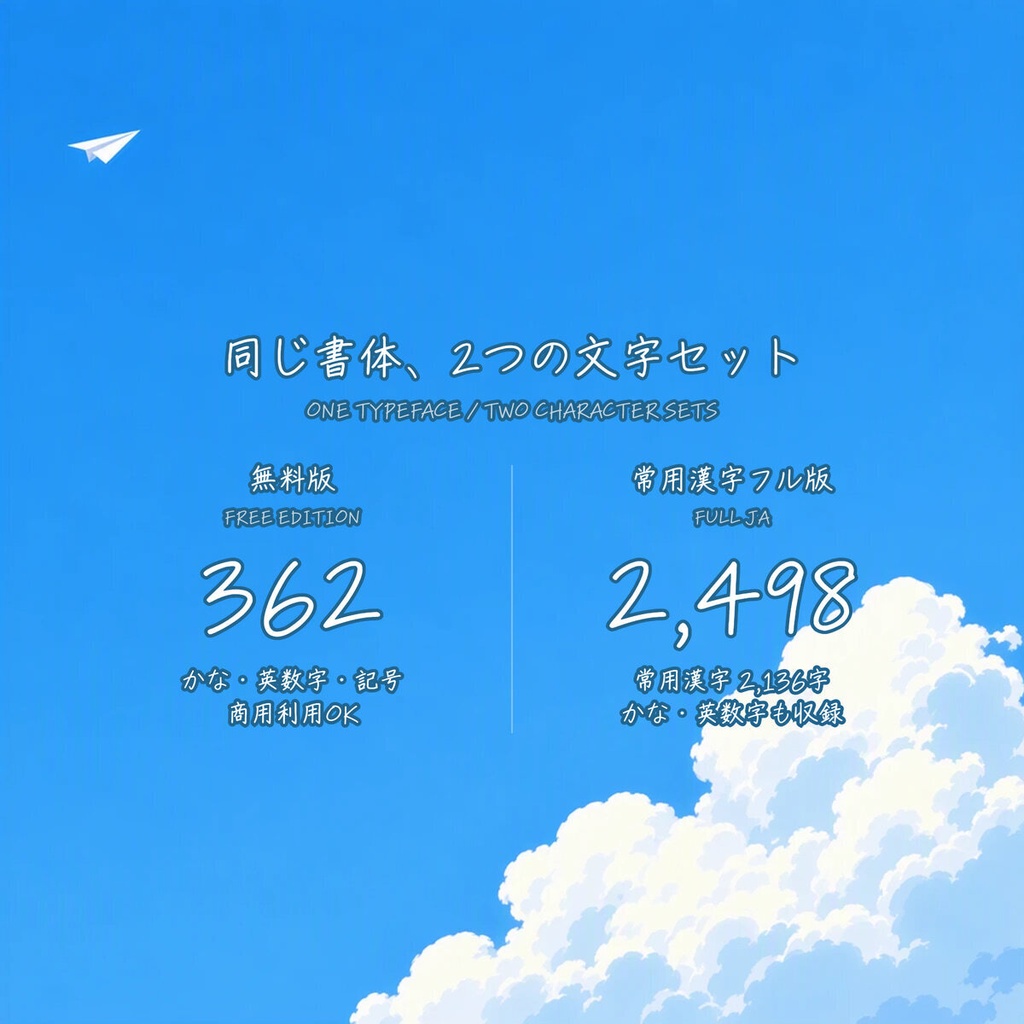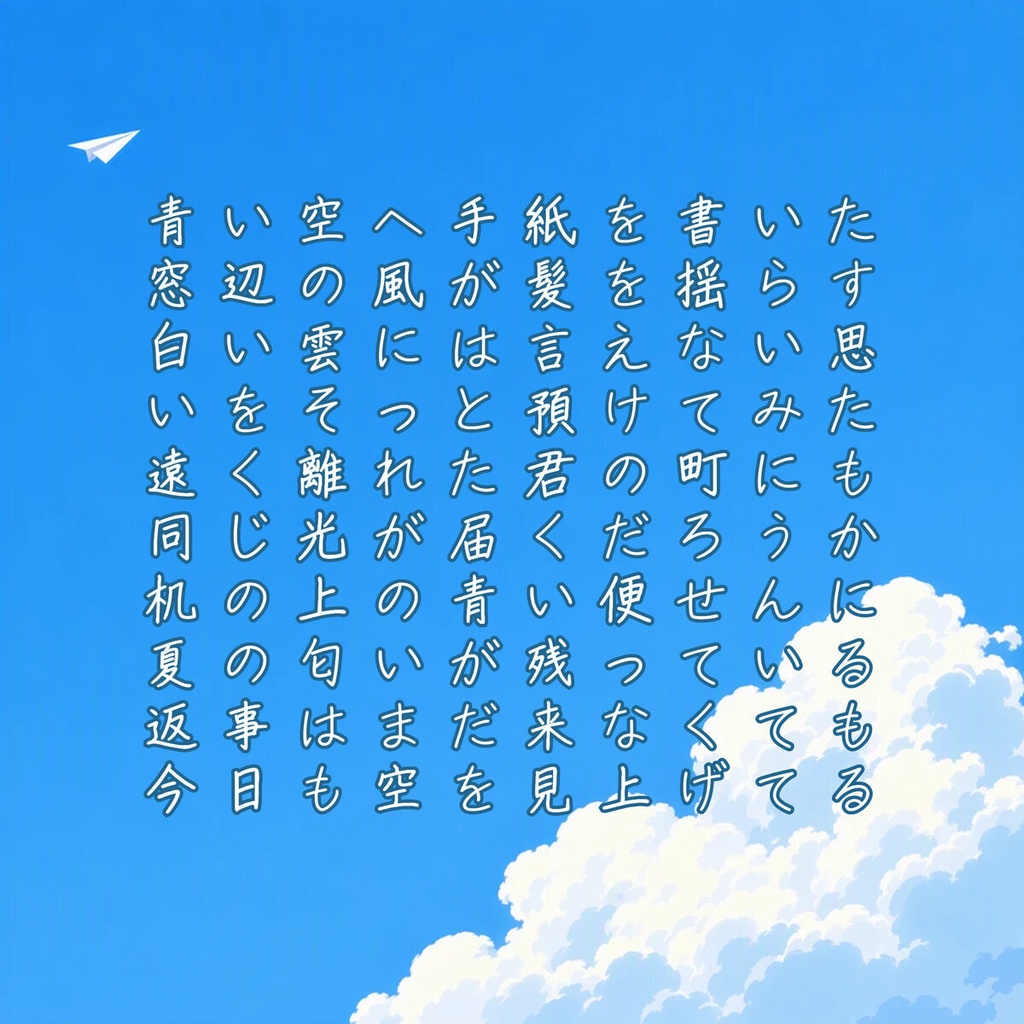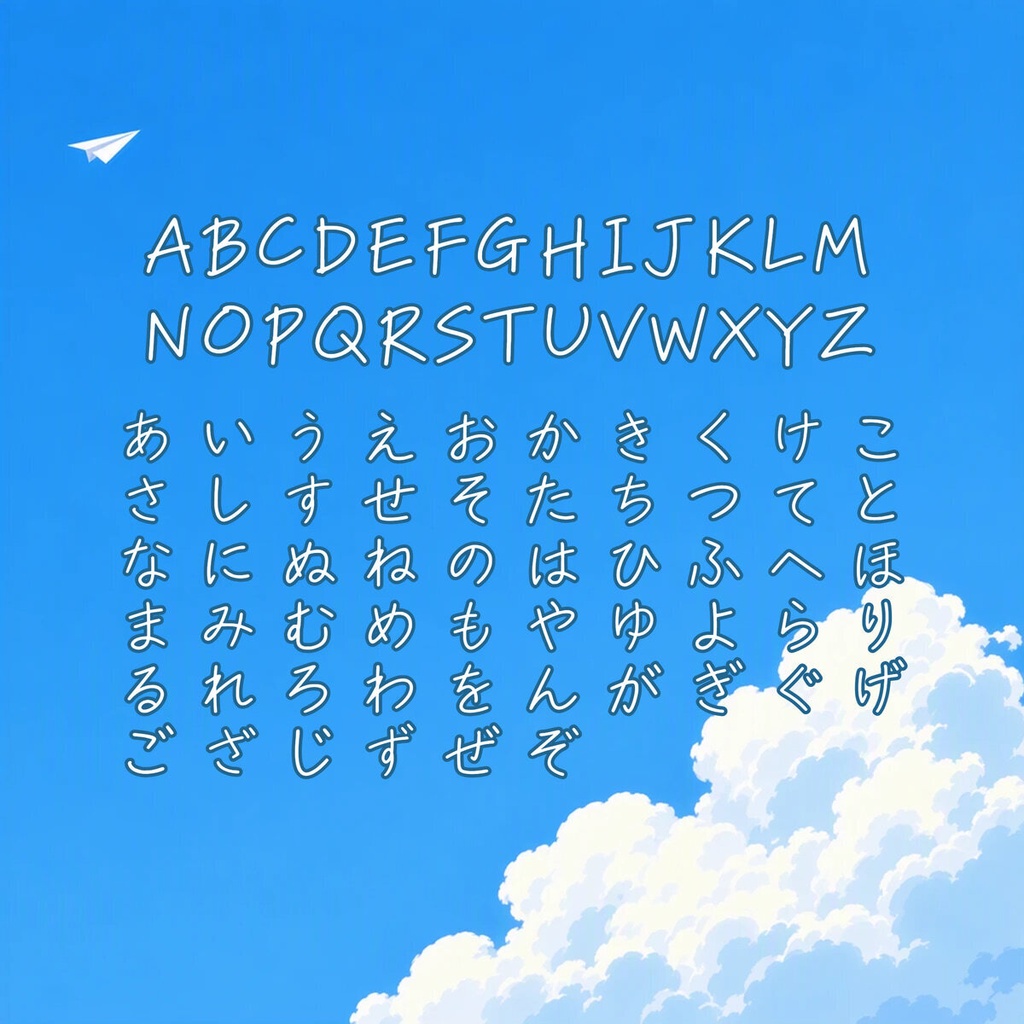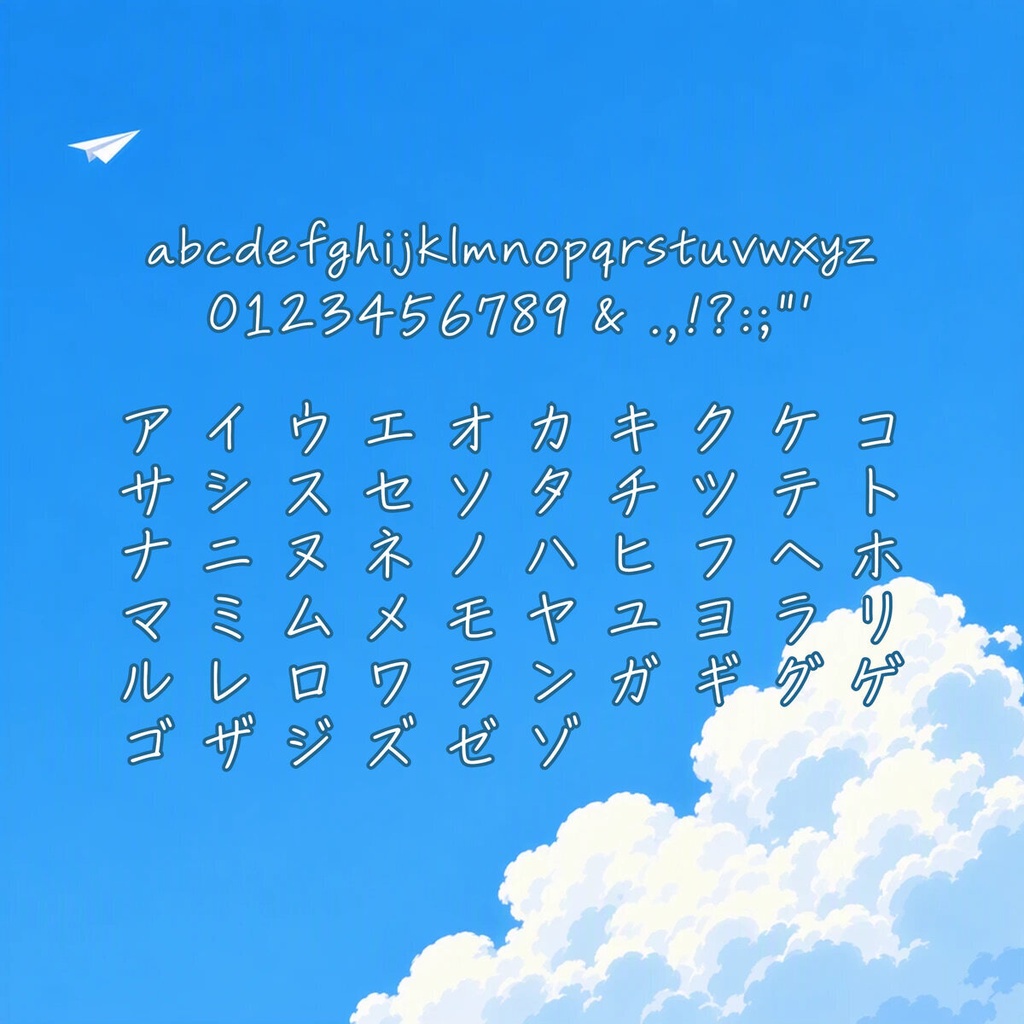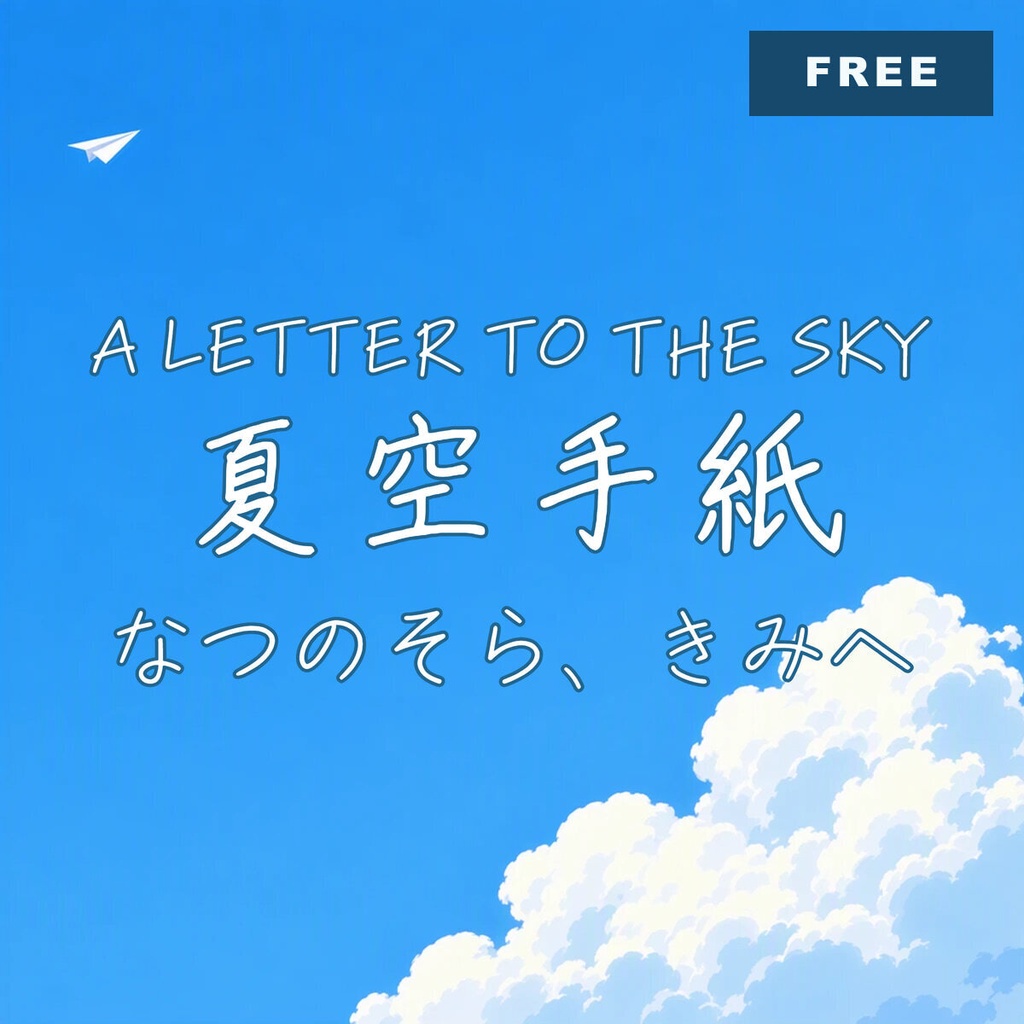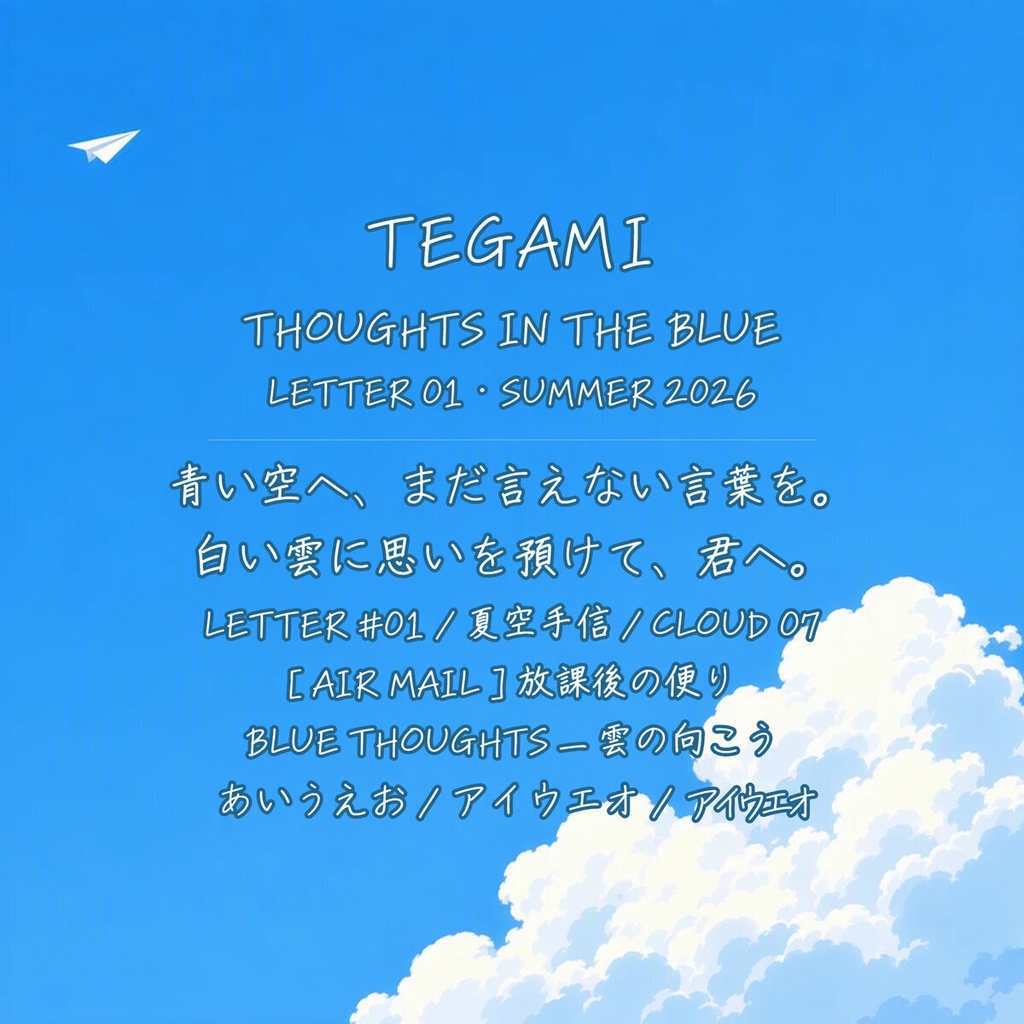
手紙 Tegami Standard【フォント】|かな・英数字301文字
青空へ送る手紙のような、軽く自然なペン手書き書体です。 A light, natural pen-handwriting typeface, like a letter sent into the blue sky. 【用途 / Use】 手紙 / 日記 / 青春作品 / 動画字幕 / ロゴ / 同人誌 For letters, diaries, coming-of-age stories, video subtitles, logos, and indie books. 【スタンダード版 / Standard】 ラテン文字・ひらがな・カタカナ・記号を全301文字収録しています。漢字・半角カナは収録していません。 Includes 301 characters covering Latin, hiragana, katakana, and punctuation. Kanji and half-width kana are not included. 301文字 / characters 【関連する収録版 / Other Edition】 常用漢字2,136字を含む常用漢字フル版もあります。 The Joyo Complete edition also includes all 2,136 Joyo kanji. ▶ 常用漢字フル版 / Joyo Complete: https://mojiworks.booth.pm/items/8860789 【フォント仕様 / Specification】 バージョン / Version: 1.0.1 形式 / Format: TrueType (.ttf), Web (.woff2) 対応環境 / Platform: Windows, macOS, web browsers 収録字一覧 / Character list: CHARSET.txt 同梱 / Included: font files, README, LICENSE, character list, portfolio PDF, product previews. 【利用規約 / License Summary】 個人・商用利用可。1ライセンスは購入者1名に適用されます。 Personal and commercial use is permitted. One license covers one purchaser. 印刷・動画・ロゴ・グッズ等の静的成果物、および購入者が運営するサイトでの同梱WOFF2の利用が可能です。 Static output such as print, video, logos, and merchandise is permitted. The bundled WOFF2 may be used on a website owned or operated by the purchaser. ゲーム・アプリへの組み込みは、利用者が生のフォントを抽出できない形式に限ります。生のフォントを同梱する場合は別途ライセンスをご相談ください。 Game/app embedding requires protection against extraction of the raw font. Contact us for a separate runtime-embedding license when shipping raw font files. 標準ライセンスは1製品・1サイトあたり年間約100,000ユーザーまで。従業員50名超の組織を含む大規模利用は要相談。 Standard coverage is approximately 100,000 users per product/site/year. Larger use and organizations with more than 50 employees require an extended license. フォント本体の再配布・販売・貸与・変換・グリフ抽出・派生フォント制作・生成AI学習やスタイル参照は禁止です。 Redistribution, resale, lending, conversion, glyph extraction, derivative fonts, and generative-AI training or style reference are prohibited. 完全な利用条件は同梱の LICENSE.txt / LICENSE.jp.txt をご確認ください。 The bundled license files are authoritative; consult them for the complete terms. 【ほかのフォント・カスタム制作 / More Fonts and Custom Work】 フォント一覧、オーダーメイド書体、文字追加、拡張ライセンスのご相談はこちら。 Browse our catalog or contact us for custom typefaces, added characters, and extended licenses. https://mojiworks.booth.pm/